Parfois, on tourne un peu en rond avec les styles d’écriture et d’alphabets qu’on connaît. Pour varier et étendre ses connaissances en dessins de lettres, il est utile de chercher des modèles d’alphabets. Mais on peut parfois s’y perdre un peu.
Avant d’aller chercher des alphabets, un exercice que j’aime bien faire (moi-même ou que je fais faire à mes élèves), c’est partir d’une feuille blanche et chercher le maximum de type d’écritures que je connais : bruchlettering, capitales d’imprimerie avec et sans serif, script, cursive, etc
Cet exercice me permet de voir si certains styles me semblent « manquer » et comparer avec les typographies que je vais ensuite chercher sur les sites dont je vous parle dans cet article.
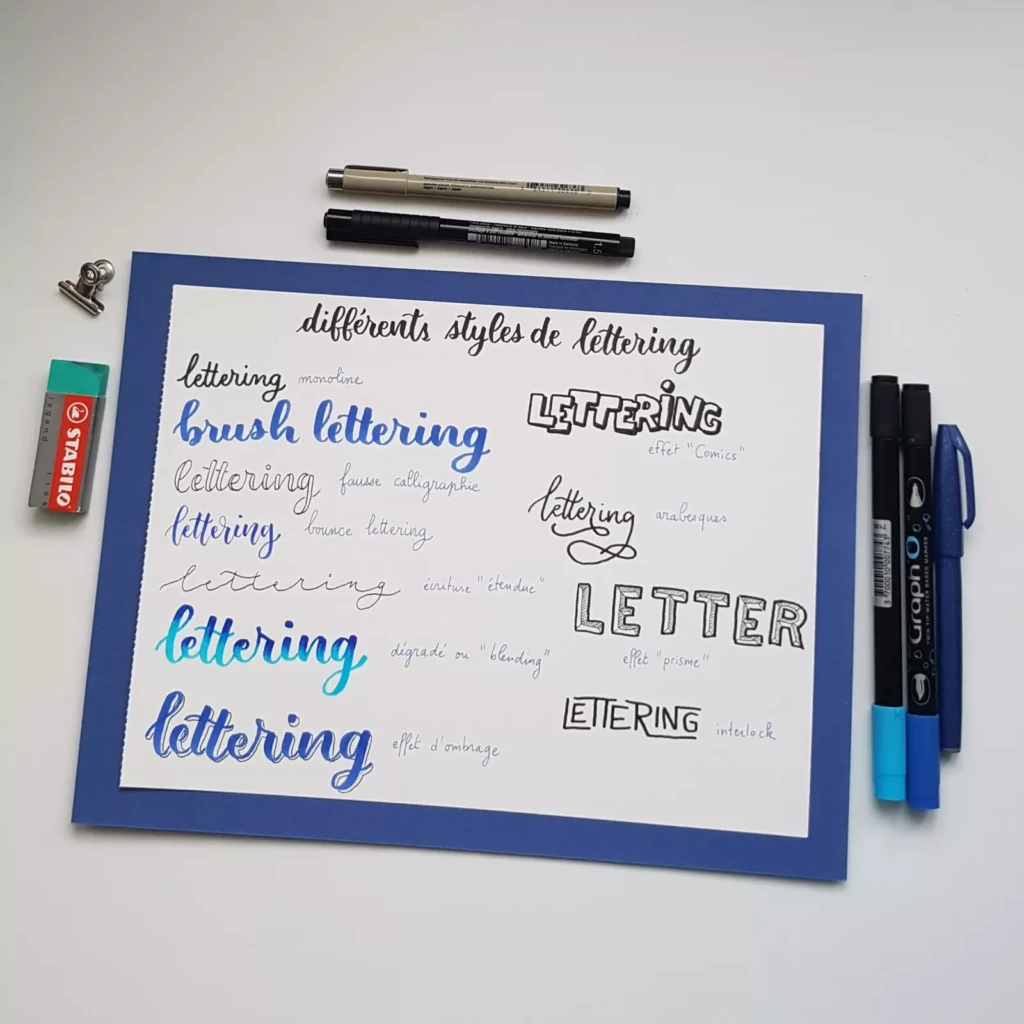
Traitement de texte de son ordinateur
Cela paraît tout bête mais regarder les polices de caractère de n’importe quel logiciel d’écriture de son ordinateur permet de voir déjà de grandes familles d’écriture. On connaît « tous » les plus classiques comme Times New Roman ou Arial. Mais c’est souvent amusant d’aller chercher d’autres polices. Je vous mets des exemples ci-dessous.
Et les recopier à la main est déjà un bon exercice et ce n’est pas si facile d’y arriver et d’avoir le même rendu qu’un ordinateur !!! On peut d’ailleurs tenter avec différents feutres et stylos, cela ne va pas avoir le même rendu.
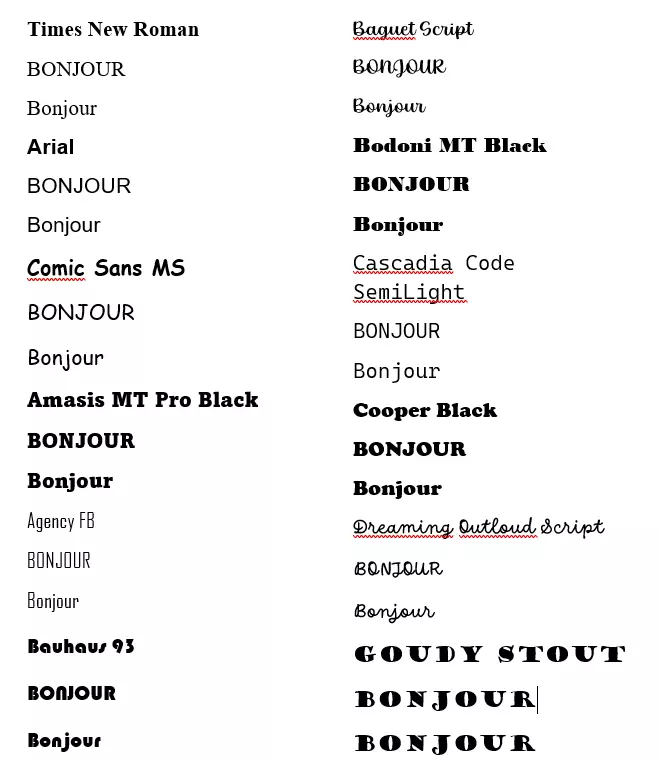
Dafont
Mon site préféré pour découvrir des alphabets, typographies et polices de caractère, c’est Dafont. Je trouve que le site est bien fait et qu’on y trouve des alphabets très variés. Cependant, on peut parfois s’y perdre alors je voulais vous montrer comment je fais pour sélectionner et conserver mes alphabets préférés !
J’ai aussi testé d’autres sites mais je les trouvais moins bien fait et, au final, un site me suffit !
Mais je vous mets quand même quelques références complémentaires !
Pinterest & Instagram
J’utilise parfois Instagram comme Pinterest c’est-à-dire comme un moteur de recherche avec des tableaux d’inspiration.
Livres pour enfants
L’univers des enfants est très riche en lettrage. Cela paraît logique car les enfants sont proches du monde de l’écriture. Ils viennent d’apprendre la lecture et l’écriture, c’est un enjeu important face à l’apprentissage, l’école, les adultes (qui ont tendance à mettre la pression sur cela !) Le rapport à l’écriture se construit dans l’enfance.
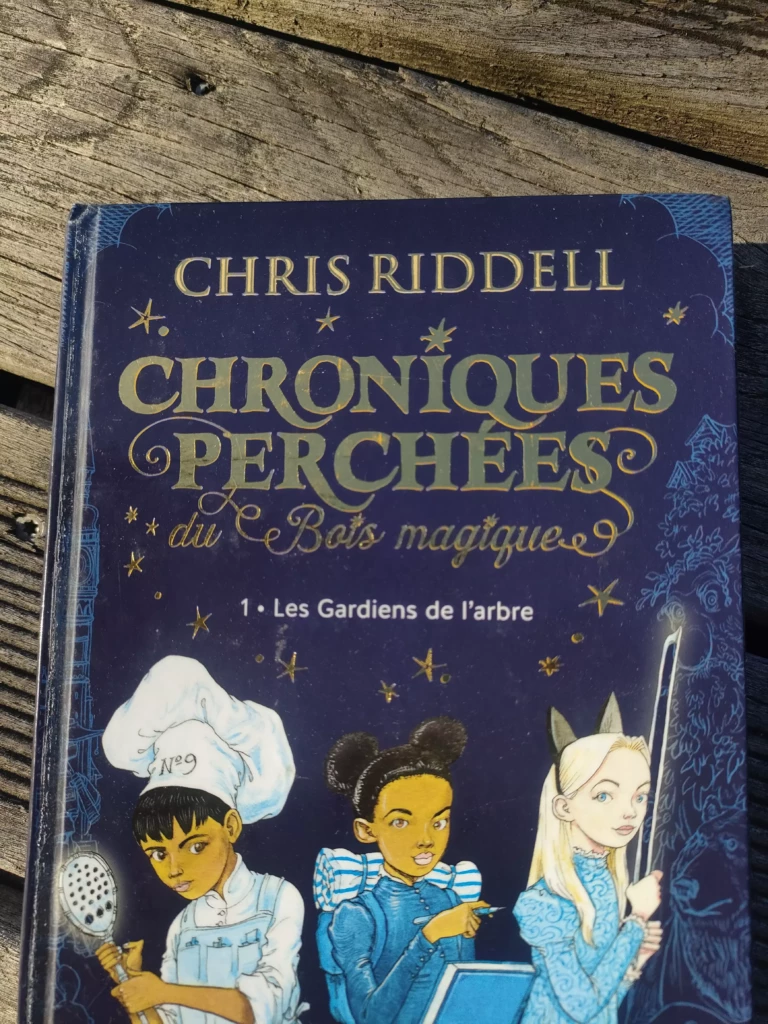
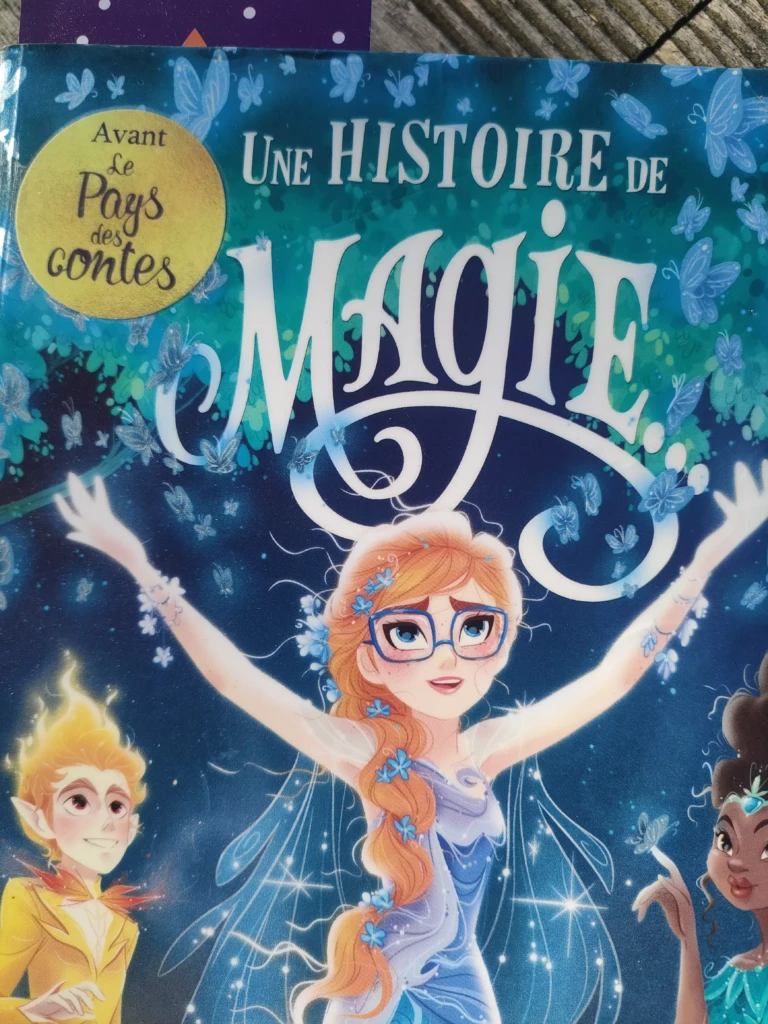
Pour aller plus loin et dans la même veine, on peut aller chercher vers les jaquettes de CD ou DVD, les affiches ou génériques de films.
Devantures de boutique et fresques murales
En me baladant dans la rue, j’ai mon capteur de lettering qui s’enclenche ! Je regarde les textes partout ! Noms de boutiques et de restaurants, affiches de festival, menus, etc.
Les lettres sont partout. À nous de les voir, les capter, les réinventer.